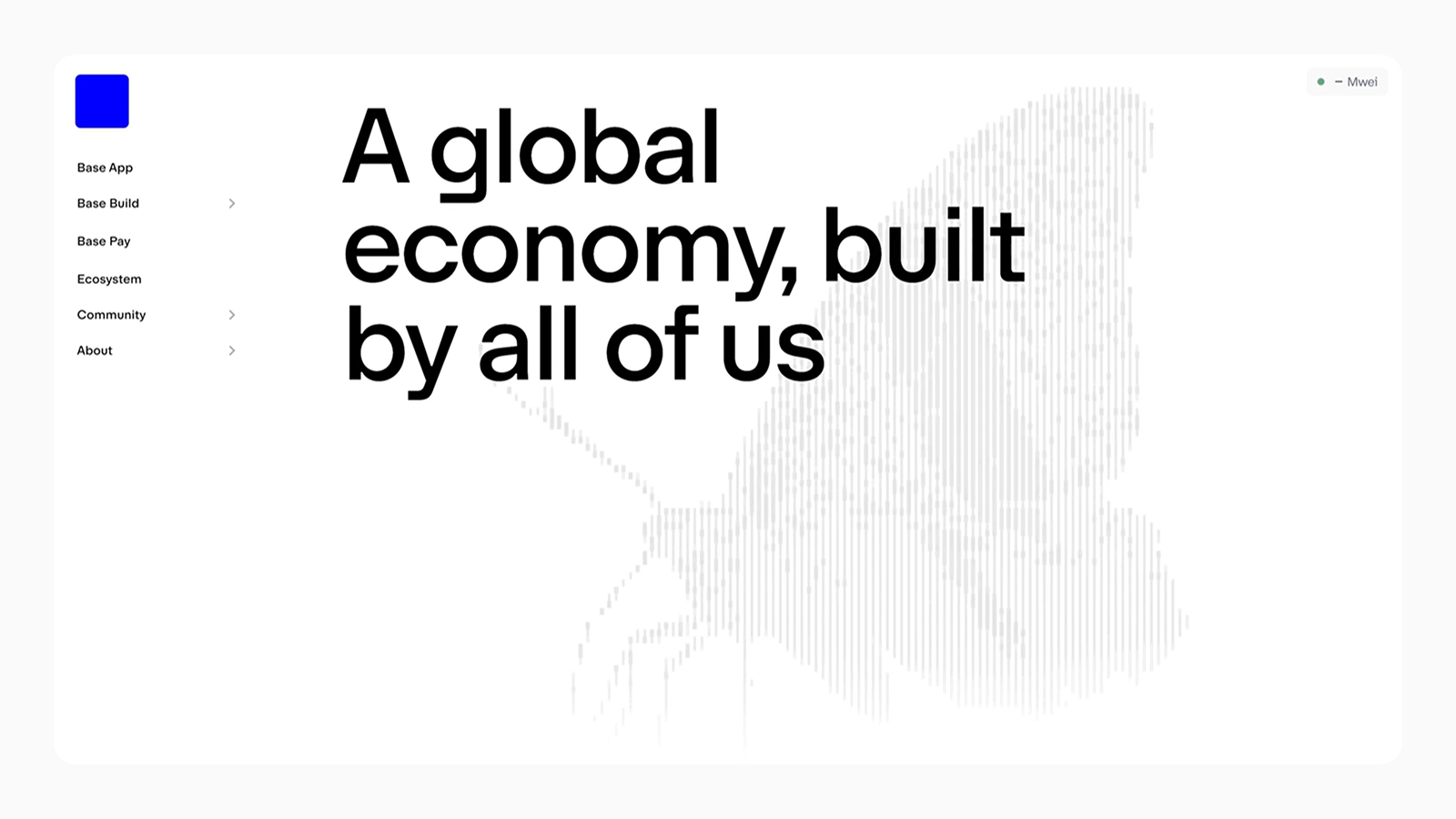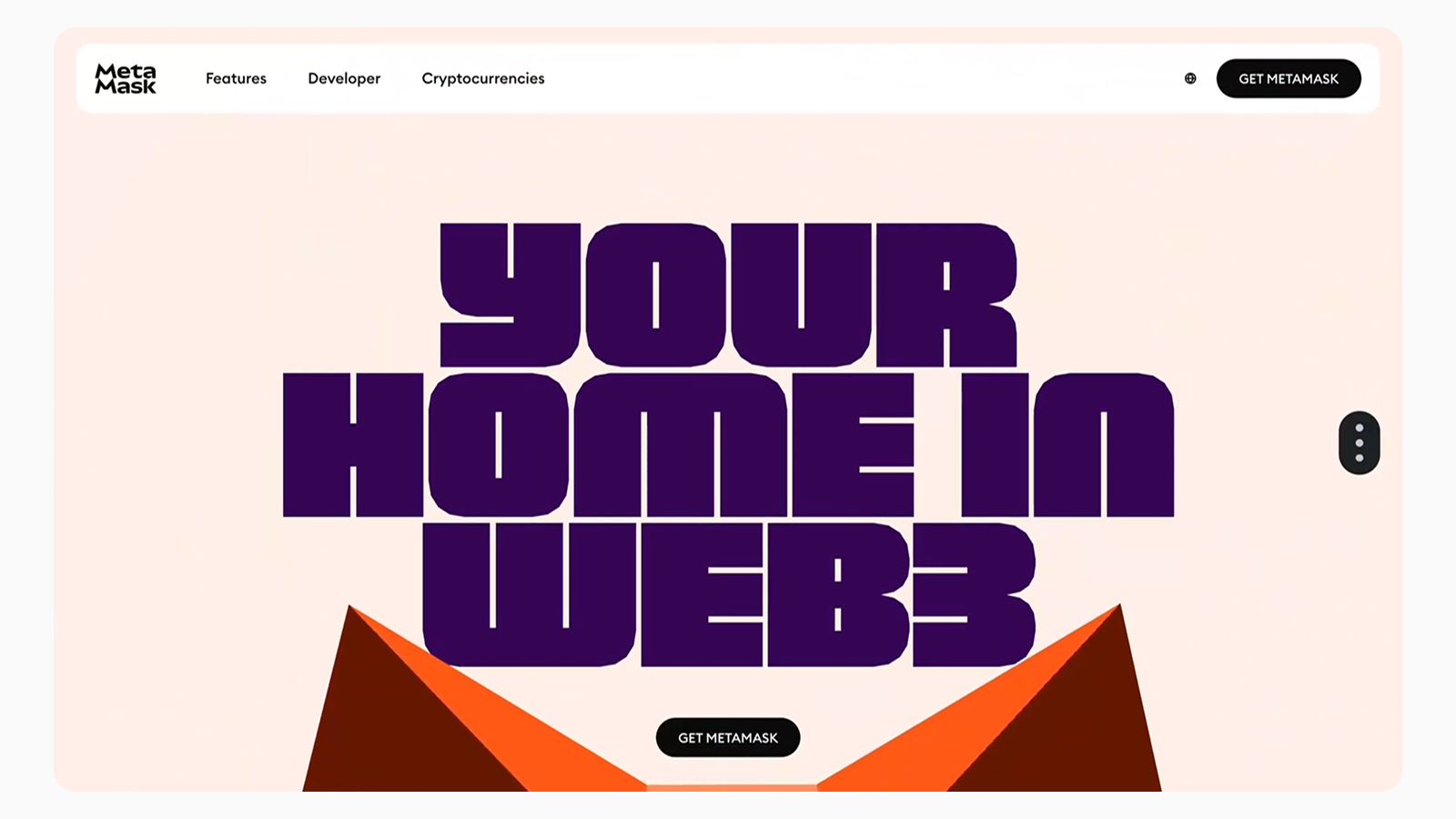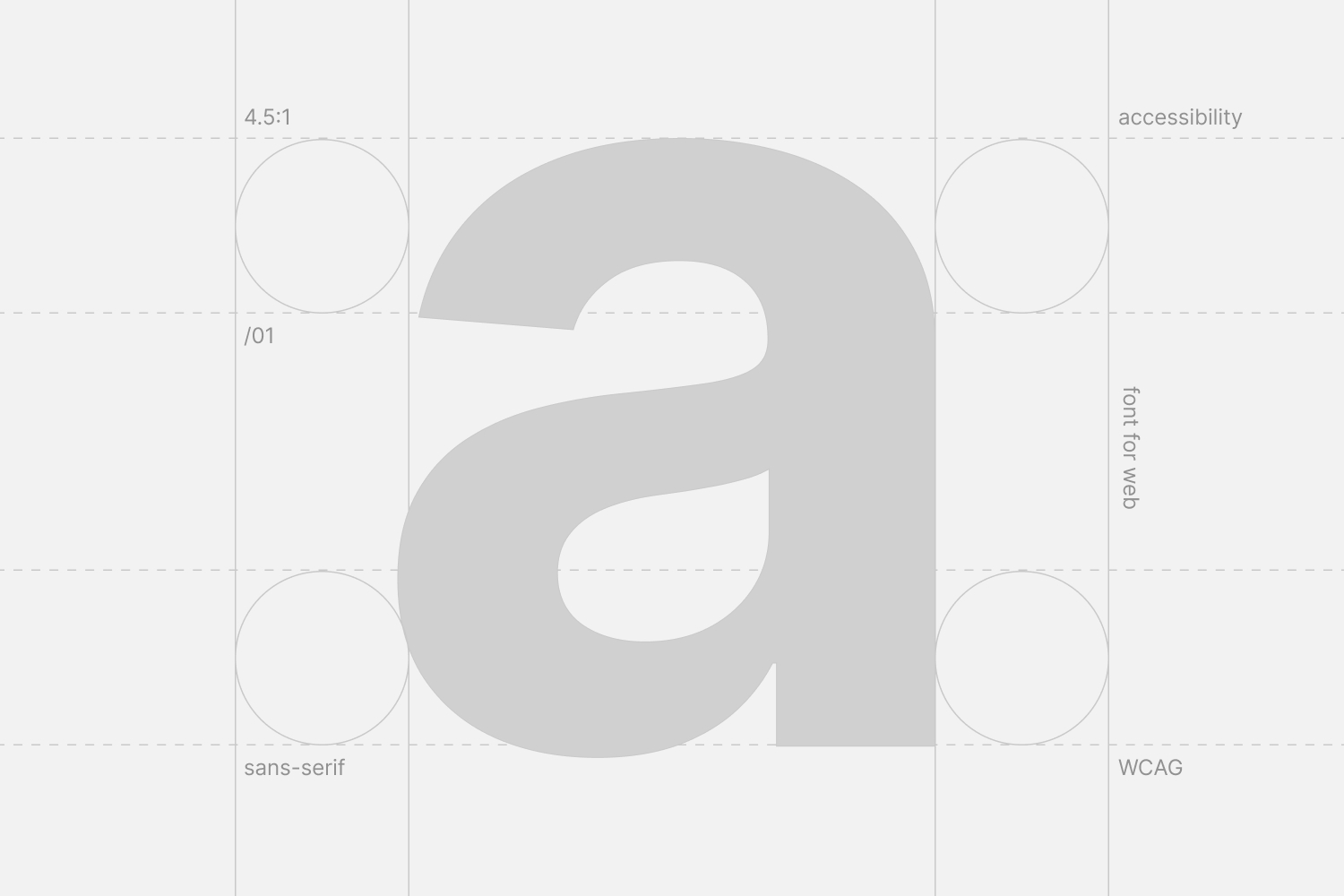
Как выбрать шрифт для сайта?
Ошибка в выборе шрифтов может сделать даже самый полезный текст невыносимым для чтения и разрушить весь пользовательский опыт.
В этой статье мы разберем пошаговый процесс как выбрать шрифт для дизайна сайта. Рассмотрим практические шаги, которые помогут тебе подобрать шрифты, которые будут поддерживать твой интерфейс и улучшать опыт взаимодействия с ним.
Что нужно знать перед подбором шрифтов?
Давай для начала определимся с некоторыми определениями. Понимание классификации и ключевых параметров — это база, на которой строятся все дальнейшие решения. Все шрифты можно условно разделить на несколько больших групп. Для веба ключевое значение имеют три из них:
Шрифты с засечками (Serif)
Засечки — это небольшие декоративные элементы на концах штрихов. Они ассоциируются с традициями, академичностью и экспертностью. Такие шрифты, как Georgia или PT Serif, отлично подходят для лонгридов и сайтов с большим объемом текста, так как засечки помогают взгляду «держаться» за строку.
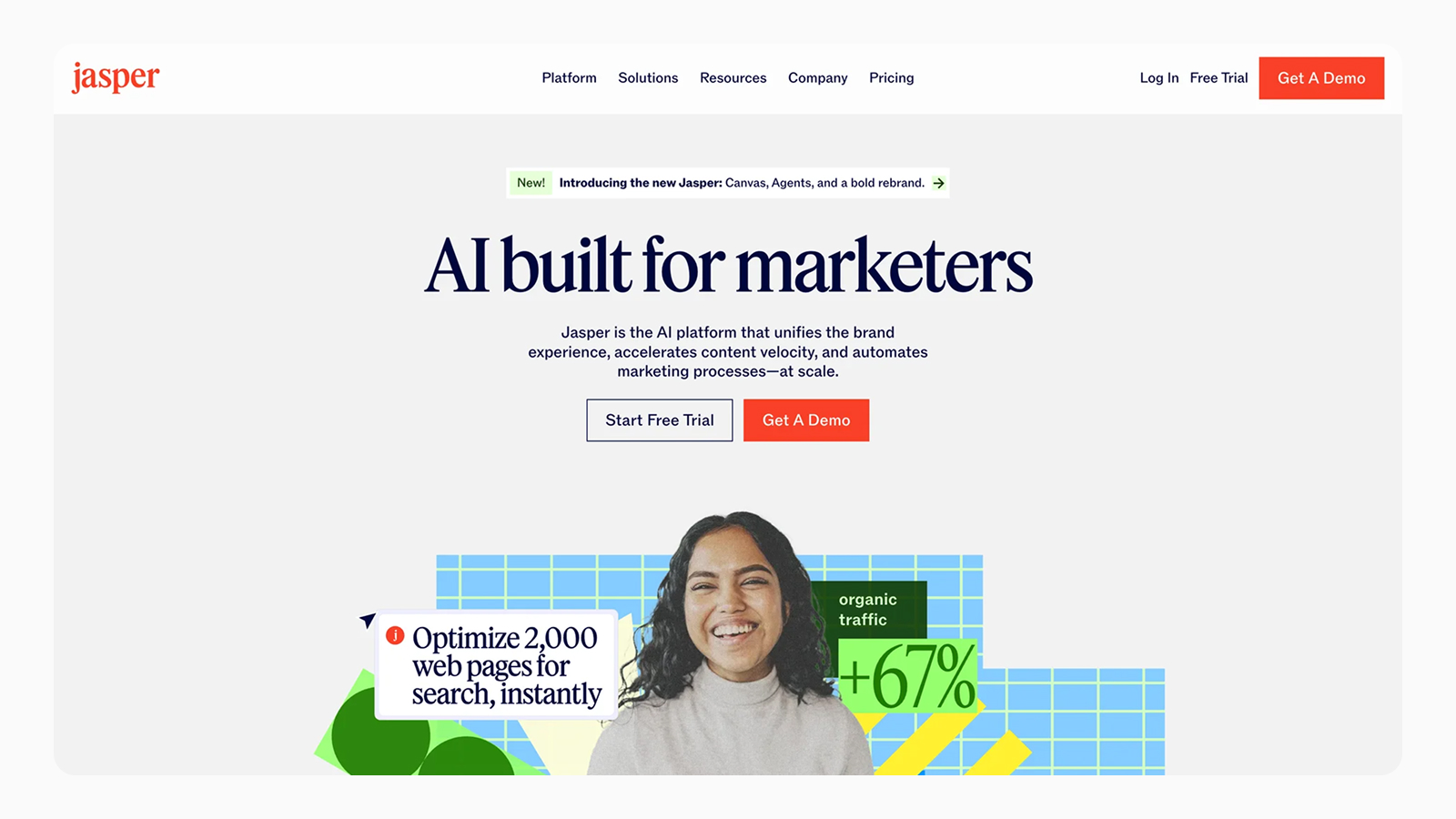
Jasper использует Serif шрифт в заголовках
Такие шрифты будут уместны на новостных порталах, образовательных платформах, юридических и консалтинговых сайтах, брендах с историей.
Это утверждение довольно спорное, но исследование NNGroup, где они сравнивали шрифты с засечками и без показало, что на современных мониторах, разница в читаемости минимальная. Камон, текст статей на сайте самой респектабельной компании в мире UX написан шрифтом с засечками 🙃
Шрифты без засечек (Sans-serif)
Эти шрифты выглядят более современно, минималистично и технологично. Текст, который ты сейчас читаешь, написан именно таким шрифтом. Они считаются более читабельными на экранах с низким разрешением. Roboto, Inter, Open Sans — классические примеры.
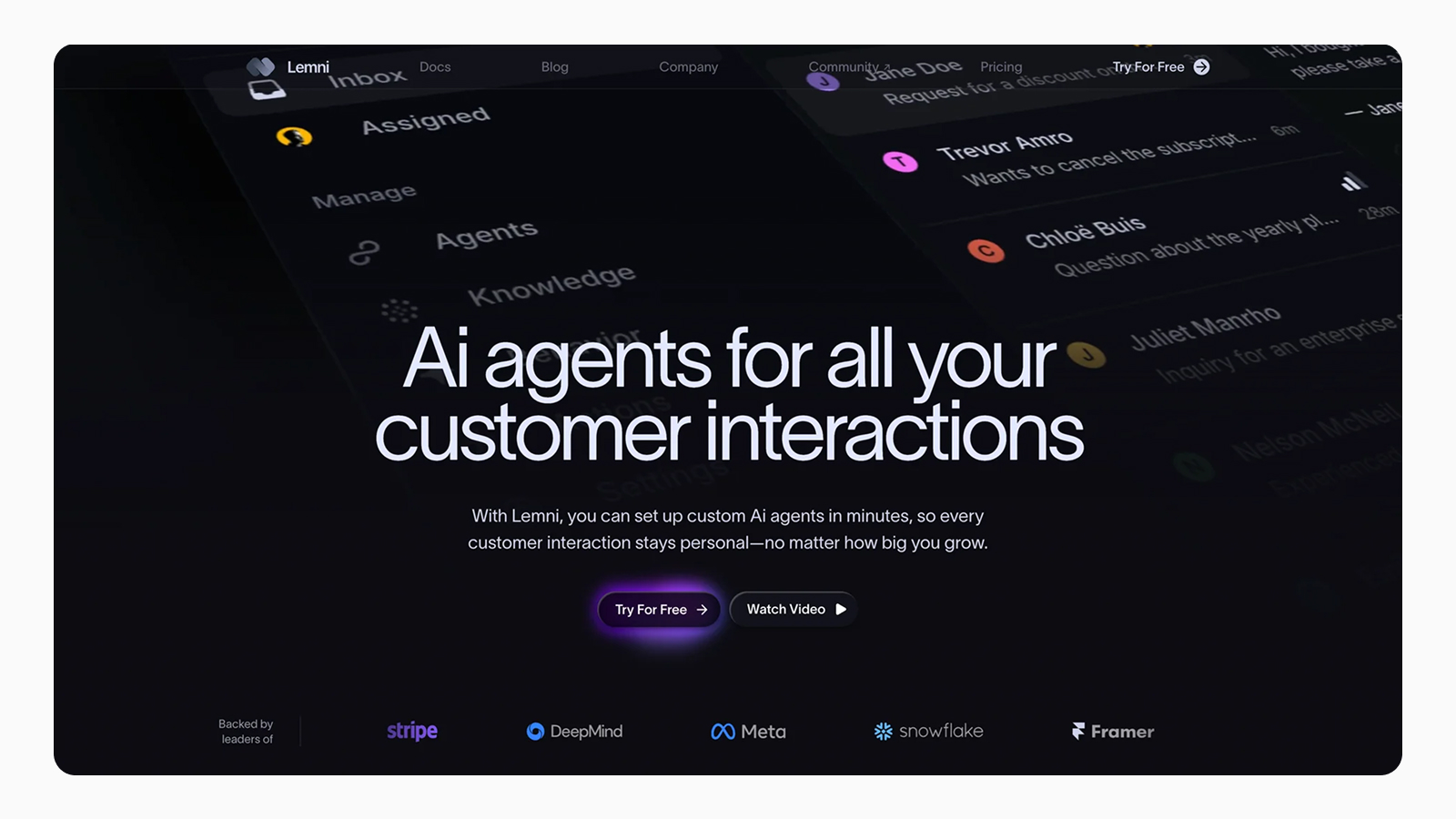
Sans-serif шрифт в интерфейсе Lemni
Применяются на сайтах-сервисах, технологических стартапах, интерфейсах приложений, корпоративных сайтах, где важна чистота и функциональность.
Акцидентные и рукописные шрифты (Display & Script)
Это декоративные шрифты, созданные для привлечения внимания. Их главная задача — быть выразительными, а не читабельными в массе текста. Использовать их для основного текста — грубая ошибка, которая уничтожит юзабилити.
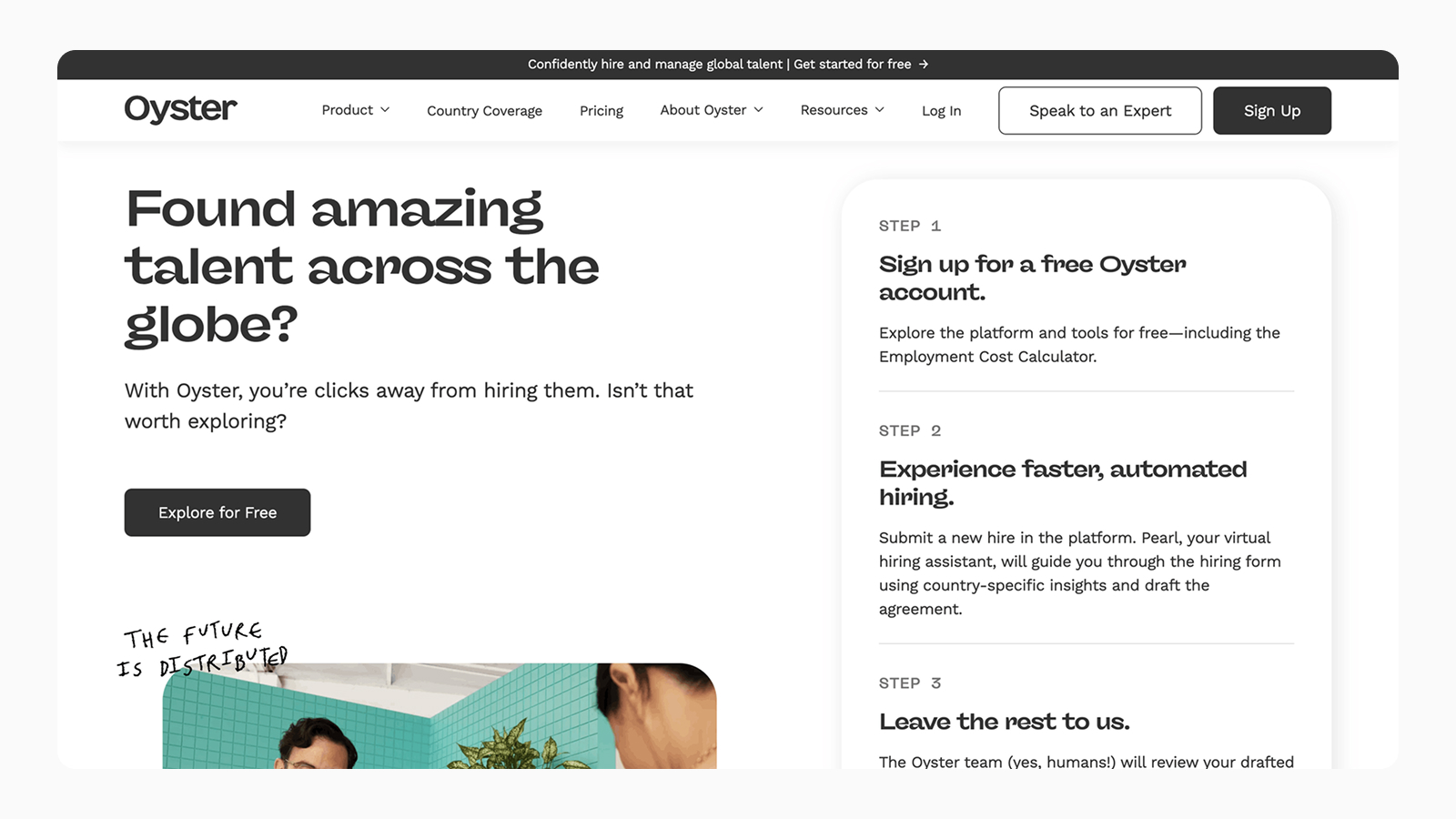
Рукописный шрифт в интерфейсе Oyster
Применяются в крупных заголовках, логотипах, рекламных баннерах, цитатах. Используйте их дозированно и не перебарщивайте.
Так же давай расставим точки над i ещё в нескольких понятиях, которые касаются типографики.
Насыщенность и начертание (Weight & Style)
Это толщина штрихов (Light, Regular, Medium, Bold) и стиль (Italic). Хорошая шрифтовая гарнитура включает несколько начертаний. Это позволяет строить визуальную иерархию без смены шрифта, делая дизайн целостным.
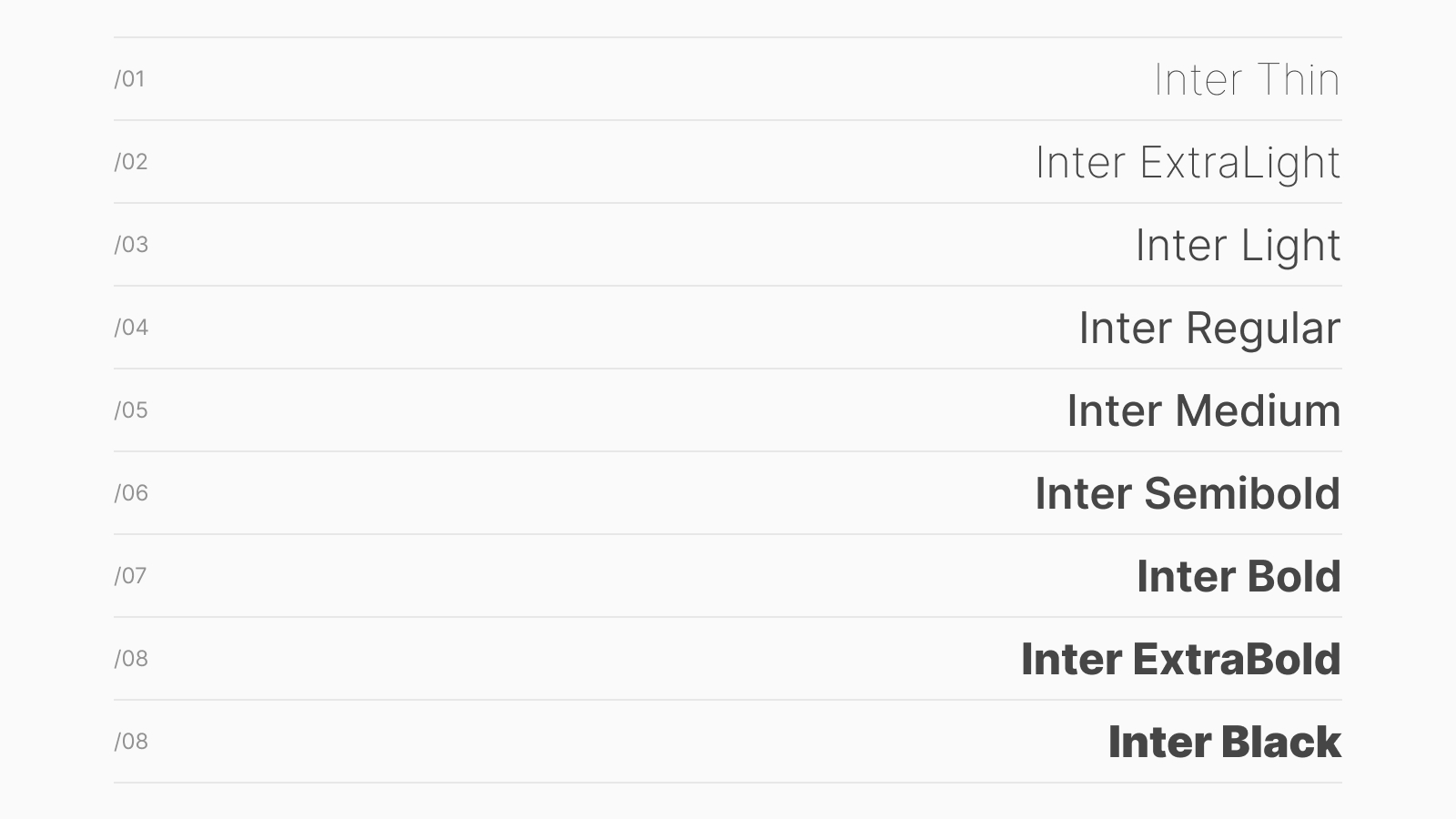
Разнообразие начертаний гарнитуры Inter
Разборчивость и читабельность (Legibility & Readability)
Разборчивость — это то, насколько легко отличить одну букву от другой, например «l» от «I» или цифру «0» от буквы «О»).
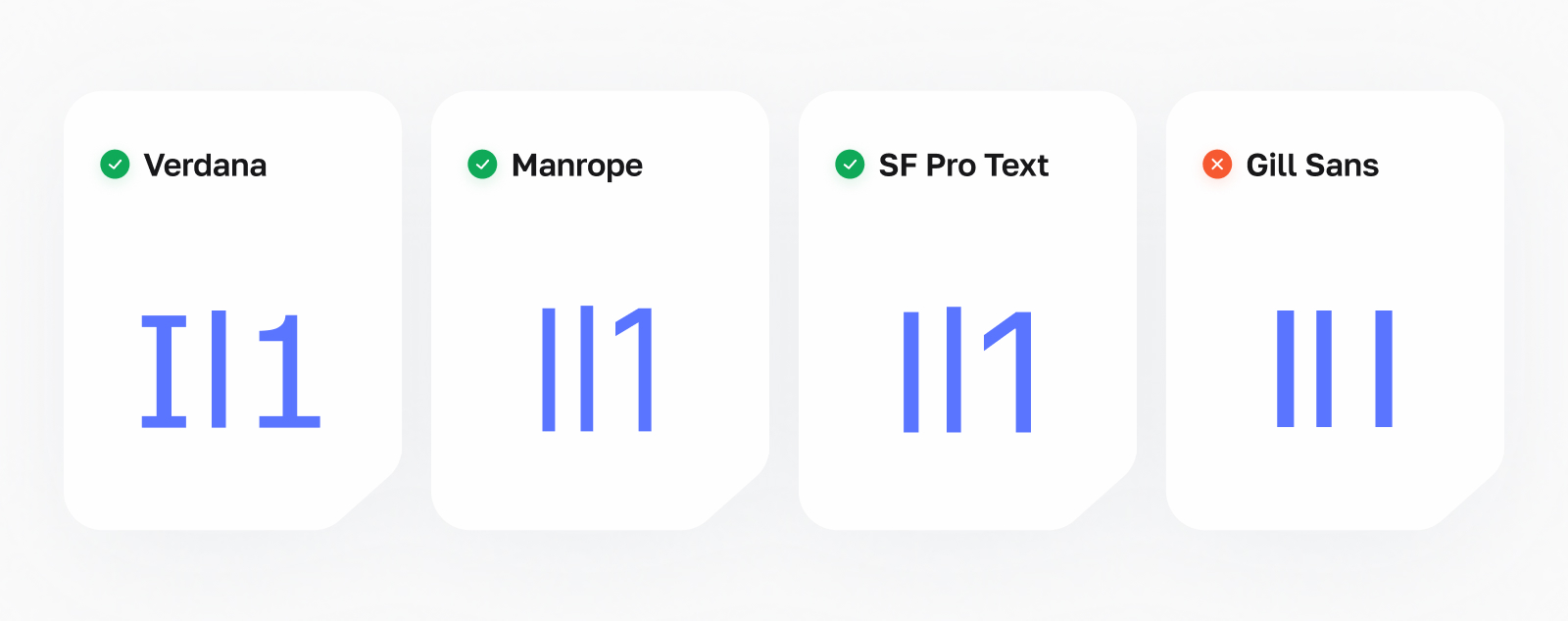
Тест на разборчивость похожих символов в шрифтах
Читабельность — это комфорт при чтении больших фрагментов текста. Она зависит не только от самого шрифта, но и от размера, межстрочного интервала и длины строки.
Для веба важны оба параметра, но при выборе шрифта для основного текста читабельность всегда в приоритете.
5 шагов в подборе шрифтов
Теперь перейдем от теории к практике. Этот алгоритм поможет систематизировать процесс выбора шрифтов для твоего проекта.
Шаг 1. Определение характера и цели проекта
Шрифт — это голос твоего бренда. Прежде чем искать шрифты на просторах Интернета, ответьте на следующие вопросы:
- Какой тон у нашего бренда? Серьезный, дружелюбный, инновационный, премиальный?
- Кто наша целевая аудитория? Что для нее будет привычным и удобным?
- Какую эмоцию должен вызывать сайт? Доверие, восторг, спокойствие?
Пример: Для сайта юридической фирмы подойдет строгий и надежный шрифт с засечками (Serif), а для детского образовательного проекта — дружелюбный и округлый Sans-serif.
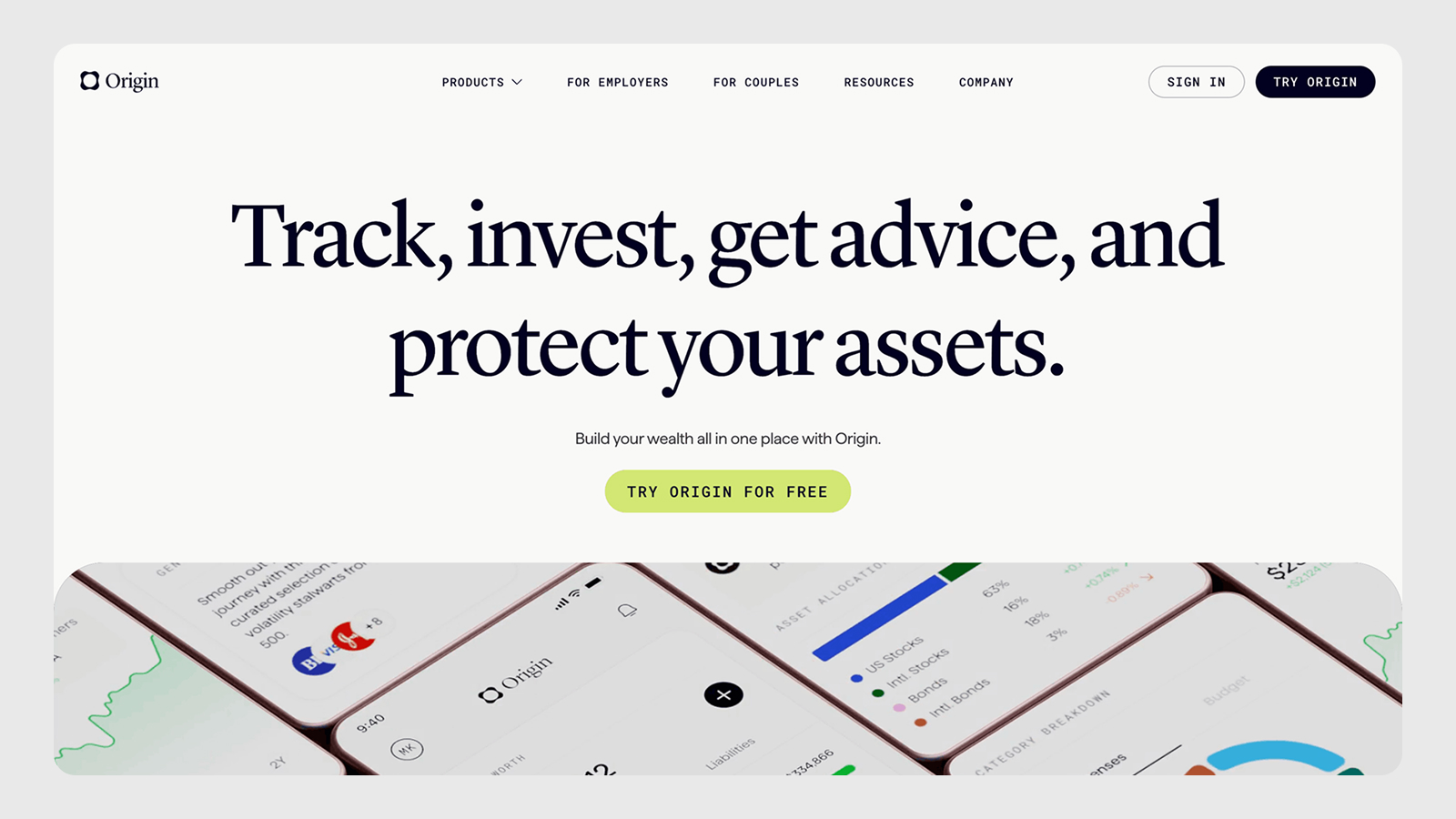
Интерфейс инвестиционной платформы Origin
Шаг 2. Выбор основного шрифта
Начинай с шрифта для основного текста. Именно его пользователи будут читать больше всего.
- Читабельность в приоритете. Выбирай шрифт, который комфортно читать в размере 16-18px. Эти размеры взяты не из воздуха, а являются рекомендациями многих организаций, занимающихся usability, например WCAG и Baymard Institute
- Проверь поддержку языков. Убедись, что шрифт поддерживает кириллицу и все необходимые спецсимволы (валюты, математические знаки и т.д.).
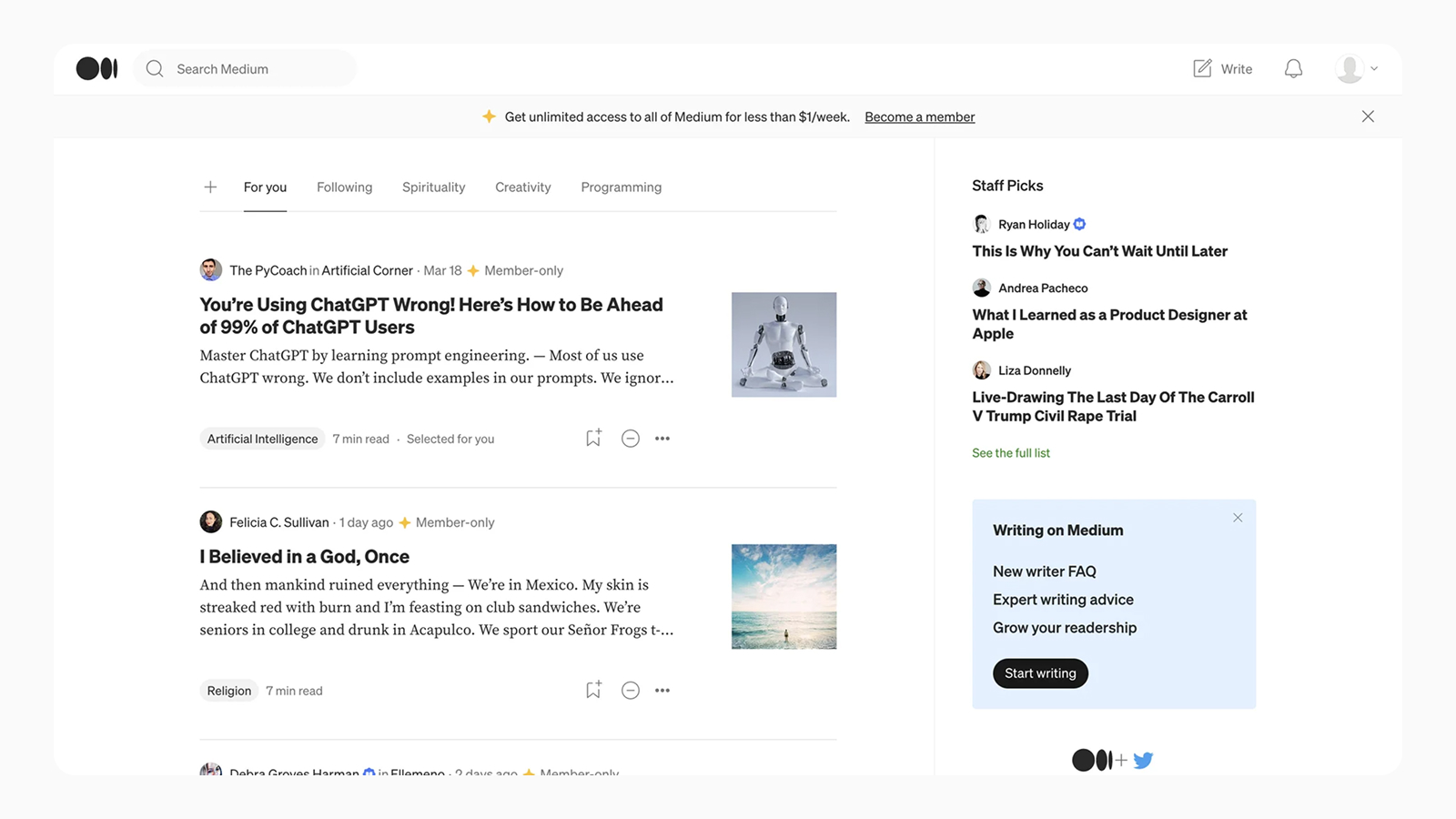
Medium использует хорошие и читабельные шрифты
Шаг 3. Создание иерархии и подбор шрифтовой пары
Когда основной шрифт выбран, подберите к нему пару для заголовков. Это поможет создать визуальный контраст и управлять вниманием пользователя.
- Принцип контраста: Самый простой способ — сочетать Serif и Sans-serif. Например, заголовок Playfair Display (Serif) и основной текст Roboto (Sans-serif).
Выбор шрифта — это системный процесс, основанный на целях проекта, понимании аудитории и технических требованиях. Начни с определения характера бренда, выбери читабельный основной шрифт, построй на его основе контрастную иерархию и не забудь о технических аспектах.
Помни, лучший шрифт — тот, который решает задачу и остается незаметным для пользователя, обеспечивая ему комфортное взаимодействие с контентом.